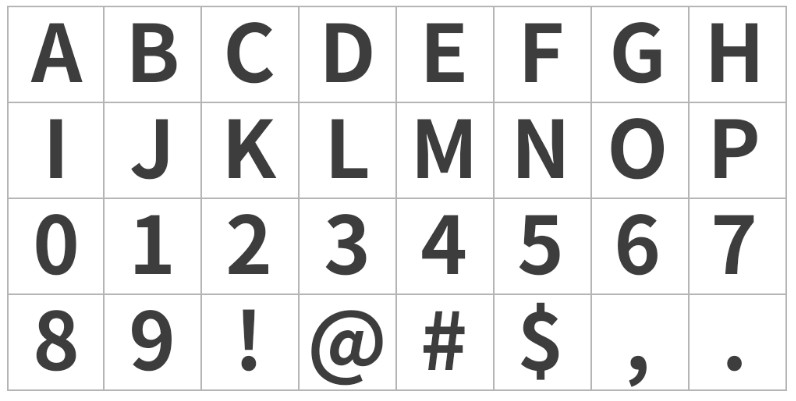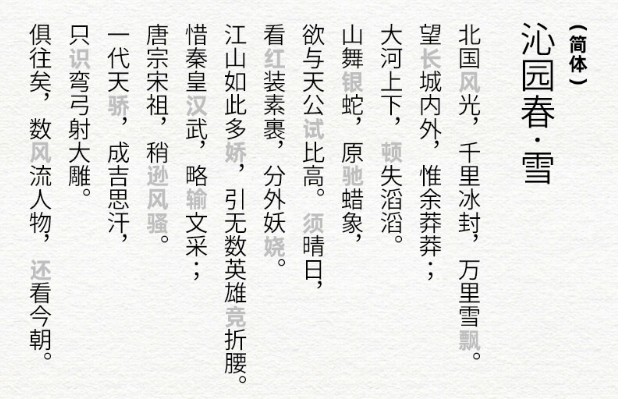
【免费商用】源真黑体21枚日本自家製フォント工房又一力作
字体名称:源真黑体PS中字体名称:源真ゴシック
字体版本:Version 1.00收录汉字:简体★★★ / 繁体★★★★★
字体背景
源真黑体( 日文名: 源真ゴシック) 是日本设计网站自家製フォント工房基于思源黑体( 日文名:源ノ角ゴシック)开发的又一款改进版黑体字型。格式上转换成 TrueType (TTF) 版,细节上也做了很多的调整与变化,使得整套字体看起来更加锐利清晰,更适用于大量文字阅读显示、代码编程、排版、打印等。
字体特色
源真黑体同样保留了思源黑体原版的优雅以及高可读性的特色,也是提供了 7 种不同的字重、3种字形样式 (包括等宽字体、比例字体)。
不过可惜的是,源真黑体是日本设计师改造的字体,因此所使用的字符集是日本的JIS标准,对简体中文支持较差,繁体支持较好。所以国内的设计师可以不必下载此套字体,因为可国内可免费商用的黑体类字体还是比较多的,例如阿里巴巴普惠体,OPPO Sans品牌字体等。